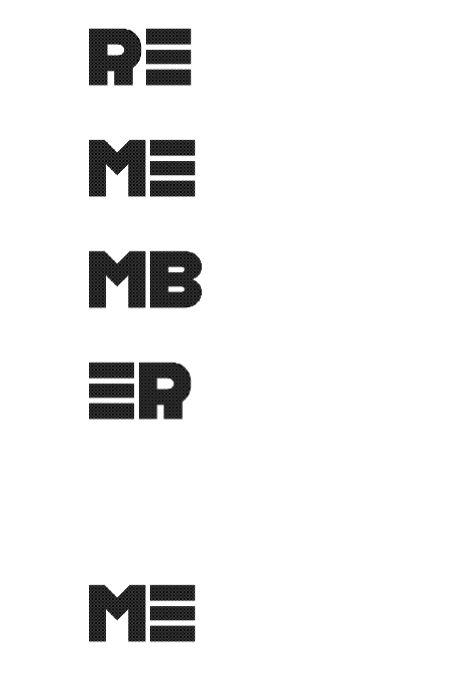
• q and 3 not finished. I just have fun with this font
Точная деконструкция. Вижу несколько идей, с которыми я играл раньше!
@TH3_C0N-MAN: Да, у тебя получился отличный шрифт. У российских дизайнеров есть тезис, что в латинских шрифтах уже всё давно изобретено, а в кириллице ещё придумывать и придумывать многие подходы, поэтому я много экпериментирую в своих шрифтах. А слабо тебе придумать что-то новое, но красивое в кириллице?
Мне очень нравятся твои цифры и шрифт в целом, мне нравится его строгий геометрический характер, но я решил сделать его ещё современней или даже слегка футуристическим, достойным этих букв А и К. Ещё я изменил Ф и Ч, теперь они привычней и потому что З слишком выделялась своей плавностью, которой не хватало в Ф и Ч. По поводу кернинга, кстати, есть такая вещь, как https://type.tools, может больше никогда не придётся вновь делать ручной кернинг) И ещё один "секрет" - для упрощения кернинга часто корректируют сами формы букв,здесь это не так удобно, как в векторе, но с такими формами J и Y можно почти отказаться от кернинга (тем более, в некоторых старых технологиях и моноширинных шрифтах он не поддерживается).
Я не понимаю конструкцию: «слабо тебе». Ты имеешь в виду, легко ли я придумаю новые формы в кириллице? Ну может быть мне нравится традиционные формы чуть-чуть больше, чем тебе.
А мне нравится твоё «Ф». Я не могу решить больше ли я люблю моё или твоё! Я тоже люблю альтернативное «Т»!
@TH3_C0N-MAN: Ты не совсем прав, что мне не нравятся "традиционные" формы, я с них начинал, например Dorojniy Sans С очень крутой, и из точек я пытался делать чистые шрифты. Просто я делаю шрифты в ограничениях Фонструктора, и не смотря на них, я уже сделал столько шрифтов, что уже почти не хватает больше фантазии и креативности, но именно деконструкции (а здесь - скорее больше стилизация) помогают расширить представления о шрифтовом дизайне и на это сейчас есть мода. Важная вещь по поводу У - для неё часто делают оптическую компенсацию, как на картинке.